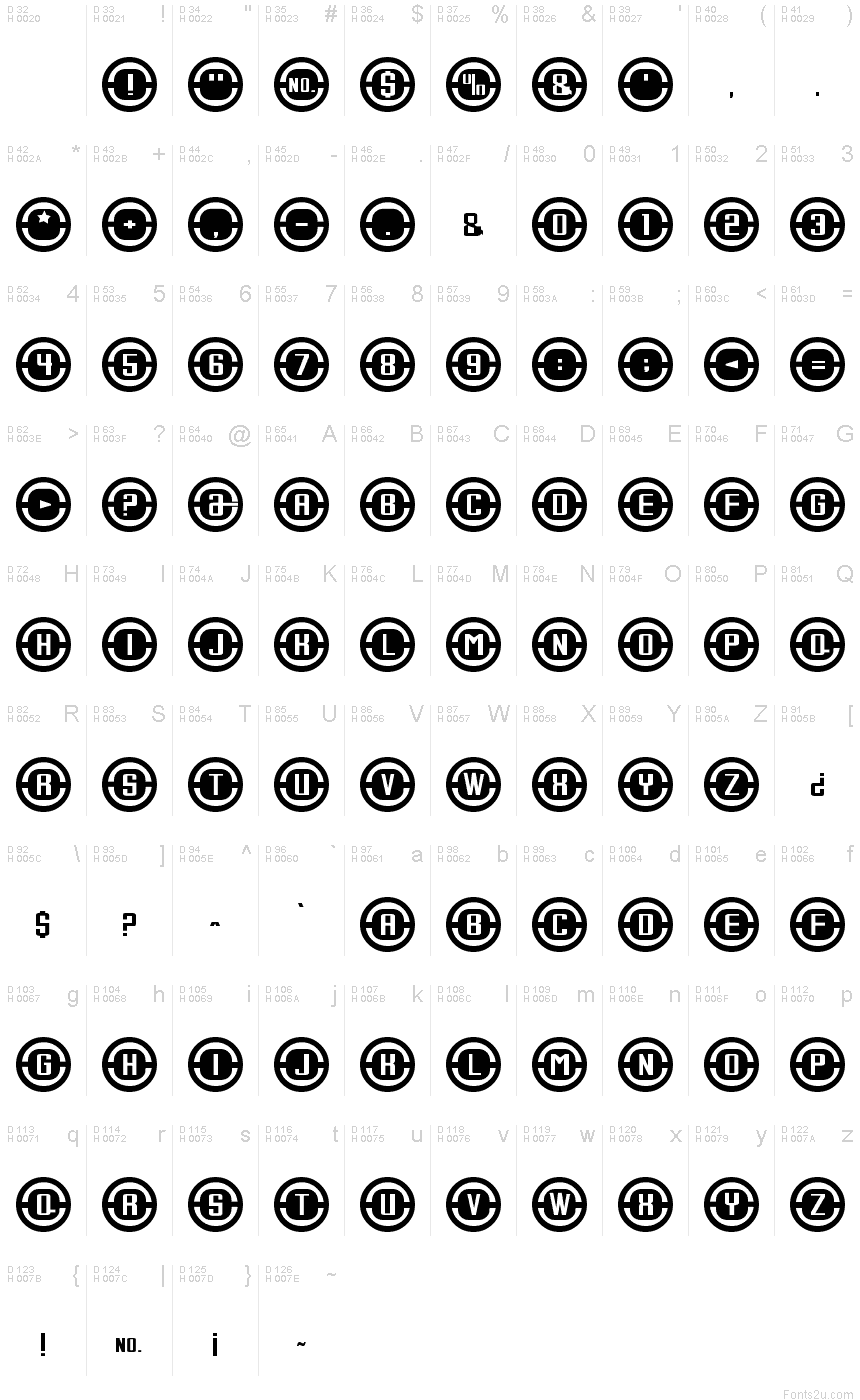
Console Relay
Console Relay to darmowy, dekoracyjny krój typu display. Jako część rodziny Console, zamyka pogrubione, geometryczne litery w grubych, kolistych formach, przedzielonych wyraźną poziomą linią. Całość przywodzi na myśl podświetlane przyciski konsol lub monety z automatów arcade – jest zwarta, wyrazista i błyskawicznie czytelna, szczególnie w większych rozmiarach.
Ten darmowy font świetnie sprawdza się w logo gier arcade, tytułach filmów science-fiction, plakatach konferencji technologicznych, identyfikacji wizualnej e-sportu, ekranach startowych aplikacji oraz naklejkach. Jego ciasny, modularny rytm tworzy silne wrażenie siatki, która stabilizuje nawet najbardziej skomplikowane układy. Połącz ten krój z prostym, bezszeryfowym pismem w tekście głównym i pozwól, by Console Relay nadał charakteru głośnym nagłówkom pisanym wielkimi literami.